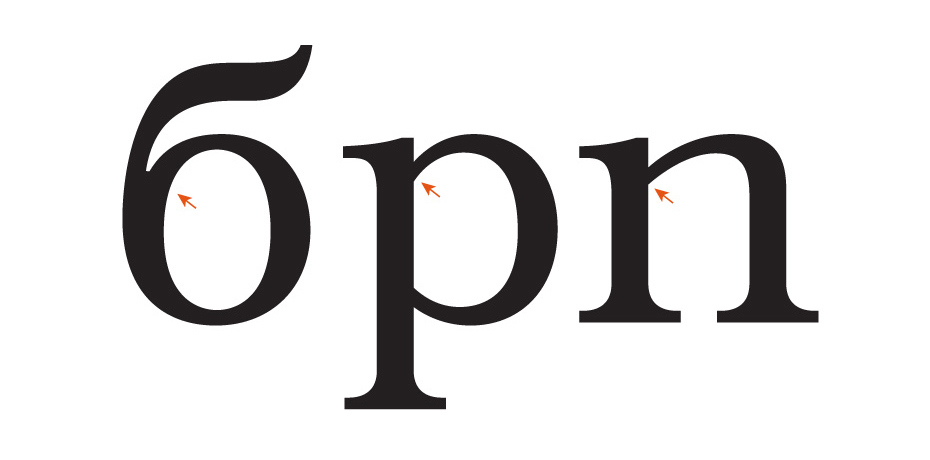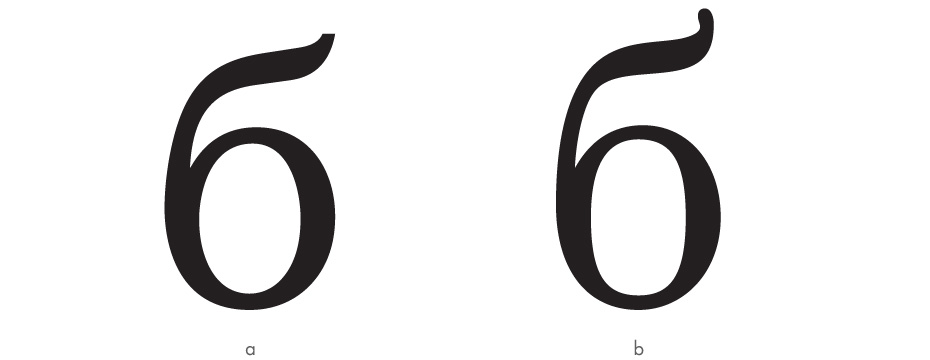
Взгляд на букву «б»
Мы от­кры­ва­ем се­рию ав­тор­ских ко­ло­нок о бук­вах ки­рил­лов­ско­го ал­фа­ви­та. Что мож­но ска­зать о бук­ве, гля­дя на неё? Толь­ко то, что её фор­ма под­ра­зу­ме­ва­ет бес­чис­лен­ное ко­ли­че­ство ва­ри­ан­тов. Но что про­ис­хо­дит, ко­гда мы срав­ни­ва­ем бук­ву с по­доб­ны­ми ей зна­ка­ми в си­сте­ме шриф­та? Фор­ма бук­вы на­чи­на­ет об­ре­тать смысл. Ди­зай­нер шриф­та Га­янэ Баг­да­са­рян де­лит­ся соб­ствен­ным мне­ни­ем о фор­мо­об­ра­зо­ва­нии од­ной их са­мых не­про­стых в ис­пол­не­нии букв на­ше­го ал­фа­ви­та. До­ба­вим, что у каж­до­го про­фес­си­о­на­ла оно «вы­стра­да­но» са­мо­сто­я­тель­но за мно­го лет прак­ти­ки, а зна­чит, субъ­ек­тив­но и мо­жет быть пред­ме­том по­ле­ми­ки.
но­гие ди­зай­не­ры ки­рил­ли­че­ских шриф­тов счи­та­ют, что удач­но на­ри­со­ван­ная бук­ва б — по­ло­ви­на сде­лан­ной ра­бо­ты. Дей­стви­тель­но, б — очень слож­ная бук­ва, от­ча­сти по­то­му, что ис­то­ри­че­ски её кон­струк­ция ещё не усто­я­лась. Но раз уж «мы здесь власть», то как на­ри­су­ем, так и бу­дет, и нам, ди­зай­не­рам ки­рил­ли­че­ско­го шриф­та, не при­ста­ло жа­ло­вать­ся на не­со­вер­шен­ство род­но­го ал­фа­ви­та, а луч­ше во­оду­ше­влять­ся тем об­сто­я­тель­ством, что имен­но это не­со­вер­шен­ство даёт нам сти­мул к но­вым по­ис­кам и экс­пе­ри­мен­там. Поз­воль­те по­де­лить­ся сво­и­ми опы­та­ми, ко­то­рые мне ка­жут­ся удачными.
Я дав­но об­ра­ща­ла вни­ма­ние на то, что бук­ва б вы­па­да­ет из ал­фа­ви­та во мно­гих шриф­тах. Ви­ди­мо, всё де­ло в том, что у неё нет ни од­но­го угла и в со­сед­стве с осталь­ны­ми зна­ка­ми ки­рил­ли­цы, со­сто­я­щи­ми пре­иму­ще­ствен­но из па­лок, она вы­гля­дит слиш­ком мяг­кой и да­же амёбо­об­раз­ной. Осо­бен­но от­чётли­во это вид­но в шриф­тах с жёст­ким ха­рак­те­ром или в чёт­ких гео­мет­ри­че­ских:
Свер­ху вниз: Charter (Мэтью Кар­тер, Вла­ди­мир Ефи­мов), Swift (Ге­рард Ун­гер, Та­гир Са­фа­ев), Futura (Па­уль Рен­нер, Вла­ди­мир Ефи­мов, Иза­бел­ла Чае­ва).
Вы ви­ди­те? Бук­ва б от­ча­ян­но про­сит пу­стить её под гри­бок, как пер­со­наж из дет­ской сказ­ки, и пы­та­ет­ся убе­дить сво­их сестёр в том, что она их род­ствен­ни­ца. Но сёстры смот­рят на­сто­ро­жен­но и не­до­вер­чи­во. И так об­сто­ит де­ло в огром­ном ко­ли­че­стве ки­рил­ли­че­ских шриф­тов. Я на­ме­рен­но вы­бра­ла всем из­вест­ные и ка­че­ствен­ные шриф­ты ра­бо­ты при­знан­ных ма­сте­ров, что­бы бы­ло яс­но, что речь идёт не о лю­би­тель­ской и не об ино­стран­ной ки­рил­ли­це. Речь идёт о не­усто­яв­шей­ся кон­струк­ции бук­вы б. Чем же мы мо­жем по­мочь на­шей бу­ков­ке с мяг­ким ха­рак­те­ром и ро­ман­тич­но раз­ве­ва­ю­щей­ся причёской?
Для на­ча­ла изу­чим су­ще­ству­ю­щие ва­ри­ан­ты кон­струк­ций. Их два. Вер­нее, два с по­ло­ви­ной. Пер­вый ва­ри­ант кон­струк­ции (а) — это, гру­бо го­во­ря, бук­ва о с при­креплён­ной к ней вет­вью. Во вто­ром ва­ри­ан­те кон­струк­ции (b) ветвь и овал име­ют об­щую спи­ну, к ко­то­рой жёст­ко при­мы­ка­ет пра­вая часть ова­ла. На­ко­нец, у вто­ро­го ва­ри­ан­та есть под­вид (с) — пра­вая часть ова­ла при­мы­ка­ет к спин­ке мяг­ко:
a — Filosofia (Зу­за­на Лич­ко, Га­янэ Баг­да­са­рян), b — Greta Text (Пе­тер Би­лак, Га­янэ Баг­да­са­рян, Алек­сей Ка­сьян), с — Didona (Вла­ди­мир Ефи­мов).
Су­ще­ству­ет ещё ру­ко­пис­ная кон­струк­ция, но в этой за­мет­ке я её не рас­смат­ри­ваю, по­то­му что с ней всё в по­ряд­ке. Итак, у нас есть два основ­ных ви­да бук­вы б. Ка­кой ва­ри­ант кон­струк­ции пред­по­чти­тель­нее для то­го или ино­го ти­па шриф­та? Чёт­ко­го от­ве­та на этот во­прос нет, но мне пред­став­ля­ет­ся це­ле­со­об­раз­ным пе­ред вы­бо­ром кон­струк­ции за­гля­нуть в со­сед­ние бук­вы и по­смот­реть, как у них при­со­еди­ня­ют­ся ова­лы к вер­ти­ка­лям: мяг­ко или жёст­ко? Ве­ли­ка ве­ро­ят­ность то­го, что вы­бор та­ко­го же спо­со­ба при­со­еди­не­ний бу­дет ло­гич­ным и есте­ствен­ным:
А иг­но­ри­ро­ва­ние это­го об­сто­я­тель­ства мо­жет при­ве­сти к то­му, что сёстры-бук­вы на­чнут со­мне­вать­ся в ис­тин­но­сти род­ства сво­ей со­сед­ки:
Не­смот­ря на то что мно­гие со­вре­мен­ные на­бор­ные шриф­ты очень да­ле­ко ушли от кал­ли­гра­фии, в кон­струк­ции зна­ков боль­шин­ства из них мож­но об­на­ру­жить ру­ко­пис­ную ло­ги­ку и пла­сти­че­скую связь меж­ду фор­мой зна­ка и пи­шу­щим ин­стру­мен­том. Если услов­но раз­де­лить кал­ли­гра­фи­че­ские ин­стру­мен­ты на две боль­шие груп­пы — ши­ро­ко­ко­неч­ные и остро­ко­неч­ные пе­рья — мож­но об­на­ру­жить, что бук­ва б со сплош­ной спи­ной по­лу­ча­ет­ся при пись­ме ши­ро­ко­ко­неч­ным пе­ром, а ветвь на тон­кой нож­ке про­ще при­ри­со­вать остро­ко­неч­ным.
Кур­сив­ная над­пись ши­ро­ко­ко­неч­ным (ввер­ху) и остро­ко­неч­ным пе­ром. Ил­лю­стра­ция: Юлия Ба­ра­но­ва.
Ко­неч­но, так по­лу­ча­ет­ся не все­гда в си­лу то­го, что ки­рил­ли­ца как ал­фа­вит ск­ла­ды­ва­лась уже в пе­чат­ную эру, и вза­и­мо­связь фор­мы её зна­ков с кал­ли­гра­фи­ей не та­кая от­чётли­вая, как в дру­гих пись­мен­но­стях. Тем не ме­нее огляд­ка на ин­стру­мент пись­ма даёт нам ещё один ар­гу­мент в поль­зу то­го, что в шриф­тах с жёст­ки­ми сты­ка­ми умест­нее вто­рой ва­ри­ант кон­струк­ции, а к плав­ным при­со­еди­не­ни­ям боль­ше по­дой­дёт пер­вый. На­ру­ше­ние этой ло­ги­ки ча­ще про­ис­хо­дит в поль­зу вы­бо­ра имен­но пер­во­го ва­ри­ан­та — он го­раз­до боль­ше рас­про­странён и вы­би­ра­ет­ся, так ска­зать, по умол­ча­нию, без осо­бых раз­мыш­ле­ний. Меж­ду тем нет ни­ка­ких осно­ва­ний счи­тать имен­но эту фор­му тра­ди­ци­он­ной (если во­об­ще пра­во­мер­но го­во­рить о тра­ди­ци­ях при­ме­ни­тель­но к по­сле­пет­ров­ской ки­рил­ли­це). Та­кая б по­яви­лась срав­ни­тель­но не­дав­но:
Эво­лю­ция ри­сун­ка бук­вы б на про­тя­же­нии XVIII–XIX вв. Под­бор­ка Да­ни­лы Во­робьёва (из ка­та­ло­гов рос­сий­ских сло­во­ли­тен).
В до­пет­ров­ской ско­ро­пи­си этой фор­мы то­же не бы­ло:
Ва­ри­ан­ты бук­вы б, вос­со­здан­ные по ис­то­ри­че­ским об­раз­цам ско­ро­пи­си. Ре­кон­струк­ция Алек­сан­дры Ко­роль­ко­вой.
Так что яв­ный ко­ли­че­ствен­ный пе­ре­вес в со­вре­мен­ных шриф­тах кон­струк­ции, осно­ван­ной на бук­ве о, мож­но счи­тать ре­зуль­та­том ско­рее сте­рео­тип­но­го мыш­ле­ния, чем осмыс­лен­но­го вы­бо­ра. Имен­но в этой кон­струк­ции нет ни од­но­го угла, и если в шриф­тах с мяг­ки­ми при­со­еди­не­ни­я­ми в свя­зи с этим не воз­ни­ка­ет ка­та­стро­фы, то в со­сед­стве с жёст­ки­ми сты­ка­ми бук­ва б при­об­ре­та­ет яв­ную амёбо­об­раз­ность. Гар­ни­тур с та­ки­ми при­со­еди­не­ни­я­ми до­воль­но мно­го — мож­но ска­зать, по­ло­ви­на из всех су­ще­ству­ю­щих: к ним мож­но от­не­сти боль­шин­ство ди­на­мич­ных шриф­тов. Но при этом бук­вы б вто­ро­го ти­па кон­струк­ции встре­ча­ют­ся до­воль­но ред­ко. А ведь в ней го­раз­до боль­ше струк­тур­но­сти.
Сплош­ная спи­на ста­но­вит­ся но­вым эле­мен­том в тек­сто­вом на­бо­ре — уни­каль­ной по фор­ме вер­ти­ка­лью. Раз­но­об­ра­зие форм — не­со­мнен­ное до­сто­ин­ство ал­фа­ви­та, а ки­рил­ли­це его яв­но не­до­стаёт. И лег­ко­мыс­лен­ный вы­бор бук­вы б, осно­ван­ной на о, толь­ко усу­губ­ля­ет од­но­об­ра­зие форм. Это мо­жет быть не­пло­хо для ста­тич­ных шриф­тов, но в ди­на­мич­ные хо­чет­ся вне­сти боль­ше драй­ва.
Кро­ме то­го, сплош­ная спи­на иг­ра­ет роль свя­зу­ю­ще­го эле­мен­та меж­ду зо­ной х-height и зо­ной верх­них вы­нос­ных. В ла­ти­ни­це эту функ­цию бе­рут на се­бя вы­нос­ные эле­мен­ты букв b, d, f, h, k, l, t, а в ки­рил­ли­це толь­ко б и ф. Если мы уберём б, ф оста­нет­ся в пе­чаль­ном оди­но­че­стве.
Я впер­вые за­ду­ма­лась обо всём этом, ко­гда ра­бо­та­ла над ки­рил­ли­за­ци­ей шриф­тов Typotheque — Fedra и Greta, и ре­ши­тель­но вы­бра­ла бук­ву б со сплош­ной спи­ной. На мой взгляд, по­лу­чи­лось впол­не гар­мо­нич­но:
А на­гра­дой, как де­серт для ди­зай­не­ра, ста­ли дис­плей­ные на­чер­та­ния Гре­ты, где у бук­вы б про­явил­ся не­ожи­дан­ный де­ко­ра­тив­ный эф­фект:
Так что я го­ло­сую в поль­зу вы­бо­ра имен­но этой кон­струк­ции в шриф­тах с жёст­ки­ми сты­ка­ми, но, ко­неч­но, этот вы­бор не дол­жен быть без­дум­ным.
И ра­зу­ме­ет­ся, са­ма по се­бе сплош­ная спи­на — ещё не за­лог ус­пе­ха, для неё ещё нуж­но най­ти точ­ную фор­му. Бук­ва не долж­на су­ту­лить­ся, а зри­те­лю на­до по­ни­мать, где за­кан­чи­ва­ет­ся вер­ти­каль и на­чи­на­ет­ся го­ри­зон­таль:
Свер­ху вниз: Titla Brus (Олег Кар­пин­ский), Linotype Pisa (Лу­тц Ба­ар, Га­янэ Баг­да­са­рян).
Это ещё не всё. Кон­струк­цию с вет­вью на тон­кой нож­ке то­же мож­но на­ри­со­вать по-раз­но­му.
a — ITC Charter (Мэтью Кар­тер, Вла­ди­мир Ефи­мов), b — Filosofia (Зу­за­на Лич­ко, Га­янэ Баг­да­са­рян).
Чув­ству­е­те раз­ни­цу? Во вто­ром при­ме­ре (b) ветвь име­ет чёт­кую кон­струк­цию и жёст­кое раз­де­ле­ние на зо­ны: тон­кий сте­бель рез­ко ло­ма­ет­ся и пре­вра­ща­ет­ся в яс­но очер­чен­ную тол­стую ветвь с од­ним опре­делён­ным дви­же­ни­ем впра­во и вверх. И так же яс­но ветвь за­кан­чи­ва­ет­ся внят­но обо­зна­чен­ной за­сеч­кой до­ста­точ­но­го раз­ме­ра. В пер­вом при­ме­ре (a) ни­че­го опи­сан­но­го нет. Ветвь де­лит­ся на зо­ны очень услов­но, ча­сто со­мне­ва­ет­ся в том, в пра­виль­ную ли сто­ро­ну растёт, и за­пу­та­лась в сво­их от­но­ше­ни­ях с за­сеч­кой. Все эти ме­та­ния ни­как не при­да­ют бук­ве уве­рен­но­сти, и в ре­зуль­та­те бо­лее успеш­ные по­дру­ги на­чи­на­ют её сто­ро­нить­ся. Срав­ни­те по­дру­жек из пер­во­го и вто­ро­го при­ме­ра:
По­хо­же, по­след­ним живёт­ся ве­се­лее.
Не бой­тесь за­вер­шить ветвь за­сеч­кой, и не сто­ит пре­не­бре­жи­тель­но к ней от­но­сить­ся, она ни­чем не ху­же дру­гих:
Свер­ху вниз: Greta Display (Пе­тер Би­лак, Ни­ко­ла Джу­рек, Га­янэ Баг­да­са­рян, Алек­сей Ка­сьян), Aldine 401 (ком­па­ния Bitstream на осно­ве ри­сун­ков Фран­че­ско Гриф­фо, Иза­бел­ла Чае­ва).
В ан­ти­квах сто­ит об­ра­щать вни­ма­ние на со­гла­со­ван­ность вет­ви б и нож­ки к. То, что они не­пре­мен­но долж­ны быть по­хо­жи­ми друг на дру­га, я не ут­вер­ждаю и ча­сто ри­сую их раз­ны­ми, но пол­ное пре­не­бре­же­ние сти­ли­сти­че­ским един­ством этих эле­мен­тов яв­но не идёт на поль­зу шриф­ту. Обыч­но в шриф­тах с мяг­ки­ми вет­вя­ми к эта вза­и­мо­связь про­сле­жи­ва­ет­ся, че­го не ска­жешь о слу­ча­ях с жёст­ки­ми нож­ка­ми, где этой риф­ме сто­ит уде­лить боль­ше вни­ма­ния. При­мер спра­ва вы­гля­дит логичнее:
Сле­ва на­пра­во: Didona (Вла­ди­мир Ефи­мов), Charter (Мэтью Кар­тер, Вла­ди­мир Ефи­мов), Greta Display (Пе­тер Би­лак, Ни­ко­ла Джу­рек, Га­янэ Баг­да­са­рян, Алек­сей Ка­сьян).
Не тре­буй­те от вет­ви обя­за­тель­ной мяг­ко­сти, она име­ет пра­во быть уг­ло­ва­той — так же, как и все осталь­ные:
Свер­ху вниз: Swift (Ге­рард Ун­гер, Та­гир Са­фа­ев), Greta Text (Пе­тер Би­лак, Га­янэ Баг­да­са­рян, Алек­сей Ка­сьян).
Ко­гда это сти­ли­сти­че­ски оправ­дан­но, пусть ветвь растёт ре­ши­тель­но вверх, не при­ну­ждай­те её гнуть­ся к зем­ле в по­ис­ках при­ста­ни­ща:
Officina Sans (Эрик Шпи­кер­ман, Оле Шёфер, Та­гир Са­фа­ев, Иза­бел­ла Чае­ва).
Раз­ре­ши­те ей быть та­кой же упро­щен­но-гео­мет­рич­ной, как и её со­сед­ки:
Brutal Type (Га­янэ Баг­да­са­рян, Дмит­рий Рас­твор­цев).
Если ветвь не по­ме­ща­ет­ся в огра­ни­чен­ном про­стран­стве верх­них вы­нос­ных эле­мен­тов, от­ни­ми­те это про­стран­ство у ова­ла, но рас­пре­де­ли­те вну­трен­нее бе­лое рав­но­мер­но и спра­вед­ли­во:
Сле­ва на­пра­во: Fedra Sans (Пе­тер Би­лак, Га­янэ Баг­да­са­рян), Rostislav (Алек­сей Че­ку­ла­ев по мо­ти­вам шриф­та Charcoal Дэви­да Бер­лоу).
Cло­вом, по­лю­би­те бук­ву б, и она все­гда бу­дет ра­дост­на, кра­си­ва и бо­дра.
Оч­ко шриф­та (x-heght) — ве­ли­чи­на строч­но­го зна­ка от­но­си­тель­но ве­ли­чи­ны про­пис­но­го зна­ка. — Прим. ред.